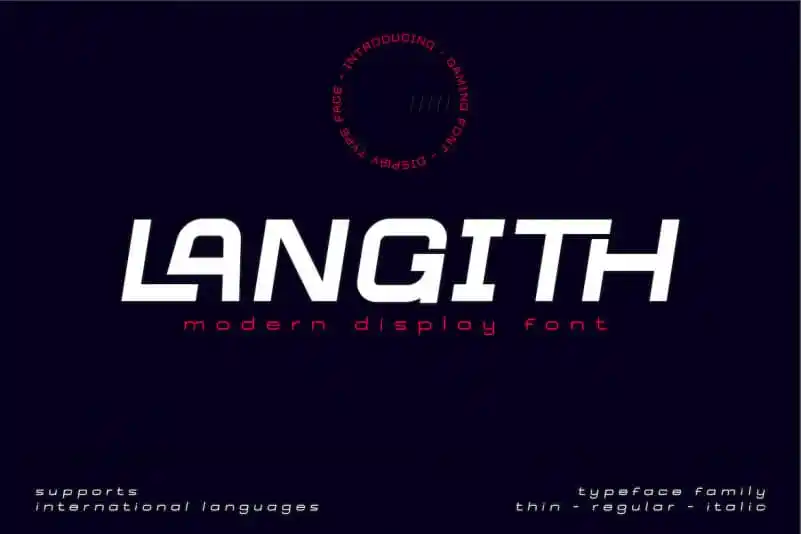
Langith Display Font – Download Grátis
Introduzimos Langith Display Font, uma família simples e limpa de san serif. Este tipo de letra não é apenas funcional, mas também possui um valor artístico evidente na forma arredondada dos seus caracteres, nas suas ângulos e no espaçamento entre letras. Uma das características mais interessantes de Langith Display é a sua capacidade de ligação (ligações), que permite criar uma variedade impressionante de designs únicos e criativos. Perfeito para aqueles profissionais de design que desejam dar um toque especial ao seu trabalho, seja em sites, cartazes ou materiais publicitários. Experimente Langith Display Font e comece a criar seus próprios designs incríveis hoje mesmo!